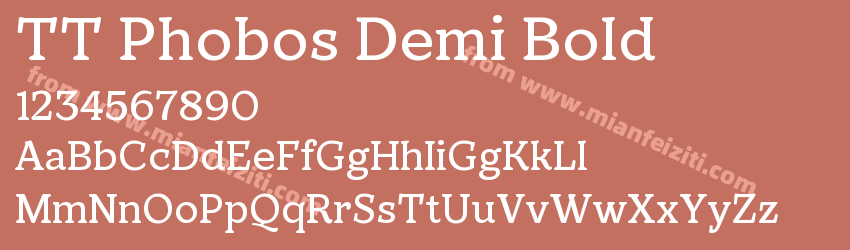
TT Phobos Demi Bold
字体名称: TT Phobos Demi Bold
Postscript名称: TTPhobos-DemiBold
字体字重: DemiBold
本款“TT Phobos Demi Bold”是一款书写很新颖的字体,字体大方,适合各种设计作品使用!欢迎下载!